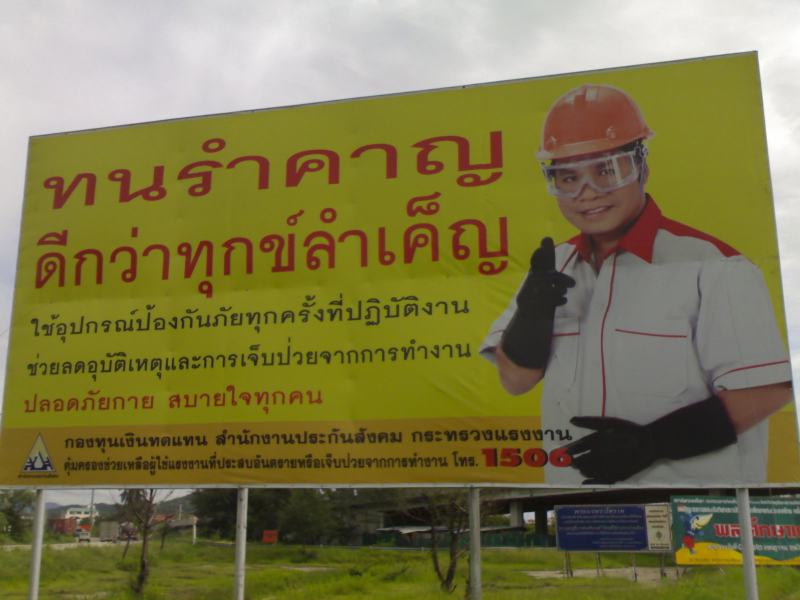
จับผิดโฆษณา
พอดีเจอป้ายประชาสัมพันธ์อยู่ป้ายนึง
เห็นมานานแล้วหละ แต่วันนี้สบโอกาสเลยสแนปภาพมาให้เพื่อนๆ
ช่วยกันจับผิดโฆษณาครับ มีตรงจุดไหนที่ผิดปกติบ้างครับ
ลองดูนะครับ สนุกๆ :22:
ปล.ขอบคุณคนออกแบบป้ายนี้นะครับ ที่ทำให้เรามีเรื่องสนุกเล็กๆ มาทายกัน
ตรงนิ้วยิ่งยงหรือเปล่าครับ :09:
ไม่เอกไม้โทบน ป ปลา เหรอ  :06:
เอ่อ คงจะผิดที่เสาครับ
เสาเล็กเกินไป ไม่มีค้ำยัน คงจะไม่สามารถรับ wind load ที่ความเร็วลมเกินกว่า 60 กม./ชม. ได้
นอกจากนั้นการใช้สีเหลือง แดง ทำให้ดูแล้วรำคาญหัวใจ
ที่เหลือคงเป็นเรื่ององค์ประกอบภาพ ที่จัดวางแล้วไม่สมดุล
สุดท้าย ที่ตอบมาไม่มีอะไรเกี่ยวกับคำถามเลย แต่อยากร่วมสนุก เผื่อได้รางวัล  :39:
ยังไม่ใช่ครับ พี่น้อง
ขำคุณแอนจัง "ตรงนิ้วยิ่งยง" :33:
เอาเป็นว่าใบ้ให้หน่อยหละว่าป๋าเลย์มาถูกทางแล้ว
แต่ยังไม่ใช่
เอ้า ! เข้ามาแสดงความเห็นหรือจุดที่ผิดปกติกันเยอะๆนะครับ สนุกดี
จะว่าไปแล้วทั้งคุณแอน กะป๋าก็ตอบถูกอะนะ แต่มันยังไม่ใช่ไฮไลท์
ที่นำภาพนี้มาตั้งคำถามอะครับ
คำว่า ปลอดภัยกาย ครับ
ใช้แค่ ปลอดภัย ก็พอ
เจ็บป่วย น่าจะเป็น บาดเจ็บ  :42:
ตัว ล ลิง ตรง "ลำเคน" หรือครับ
เห็นต่างเพื่อน
ไม้เอก ตรงคำว่า ป่วย หรือเปล่าครับ
ปกติ น่าจะเป็ย "ป่" แต่ในรูป ไม้เอกไปอยู่บนหาง ป.ปลา
ผมว่าสี background สีเหลืองน่ะ ทำไมมันคนละเหลืองอะ  :43:
แต่ที่แน่ ๆ วรรณยุกต์ล๊อย ลอย  :39:
ตัวหนังสือมันยืดๆ หดๆ (แต่ละบรรทัดความกว้างของฟอนต์ไม่เท่ากันสักตัว)
ตรงที่ยิ่งยงไม่ใช่หนุ่มโรงงานเหรอคะ :09:
ที่ยิ่งยงเอามือจับพุง